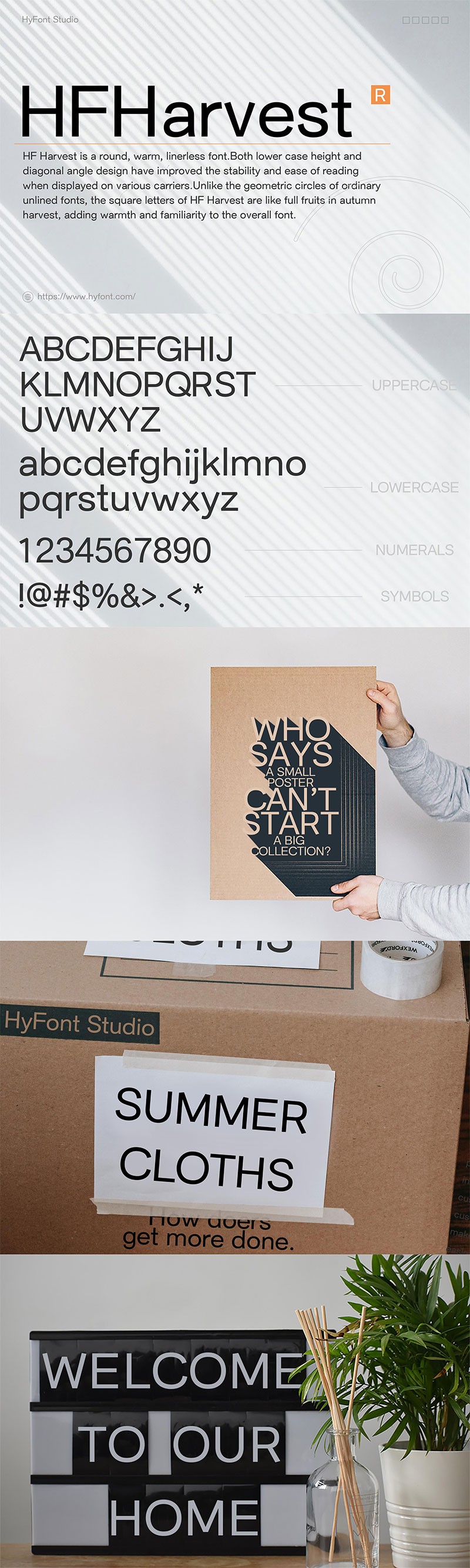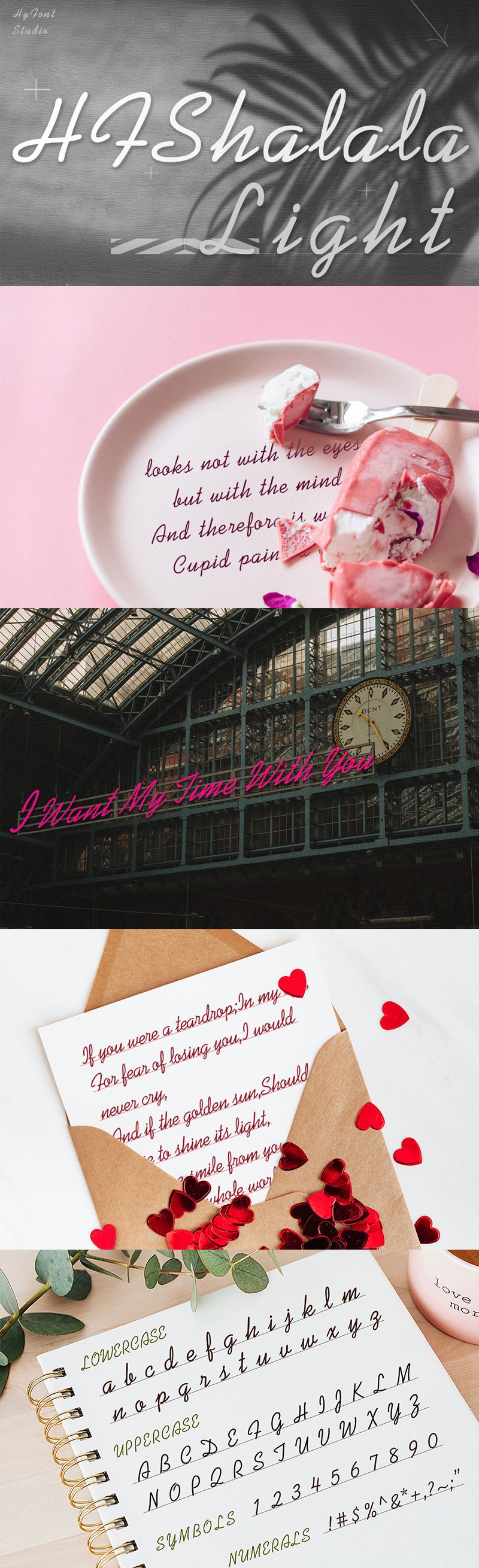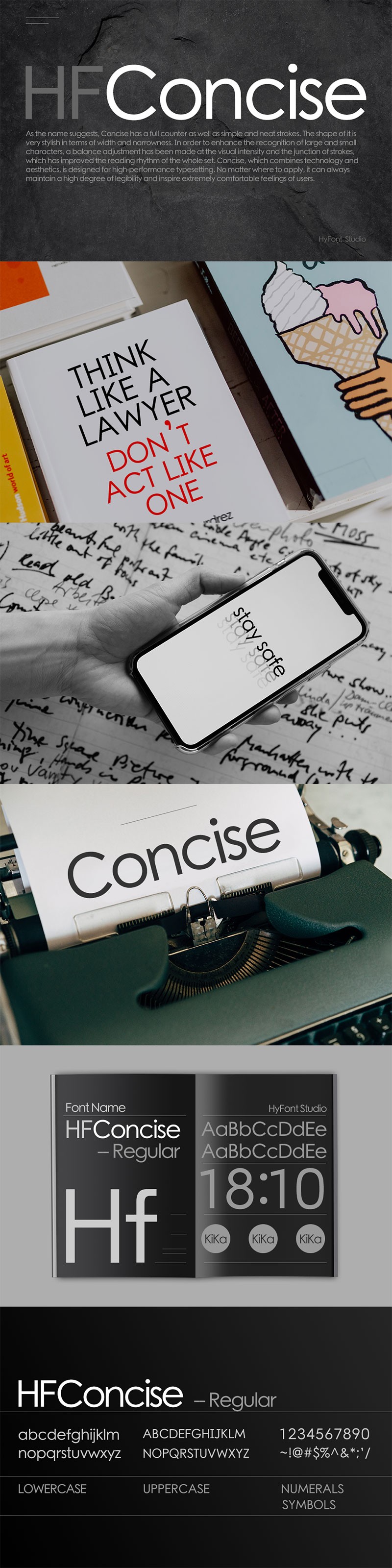
HyFont免费商用英文字体
HFConcise
一款以几何造型为灵感、融合许多优秀字体风格而研发的极具现代感的无衬线免费商用字体。字谷在网提交免费订单获取商用授权
HFHarvest
一款圆润、温暖的无衬线字体。不论是降低小写字高或是笔画斜切角的设计,各方面皆提升字体在各种载体上显示时的稳定性与易读性。字谷网提交免费订单获取商用授权
HFShalala
一款笔型圆润、优雅、温暖的免费商用手写书法字体。在自由的风格下,每个字的造型元素,仍隐约感到得到字体的规则性、规律性。字谷网提交免费订单获取商用授权
HFSiali
一款极具人文特色的手写免费商用字体。 Siali整体造型干净利落,区别传统手写体的连笔造型,优化了起笔、收笔的停顿笔触,保持每个字符的整齐从而提升整体阅读的舒适性。字谷网提交免费订单获取商用授权